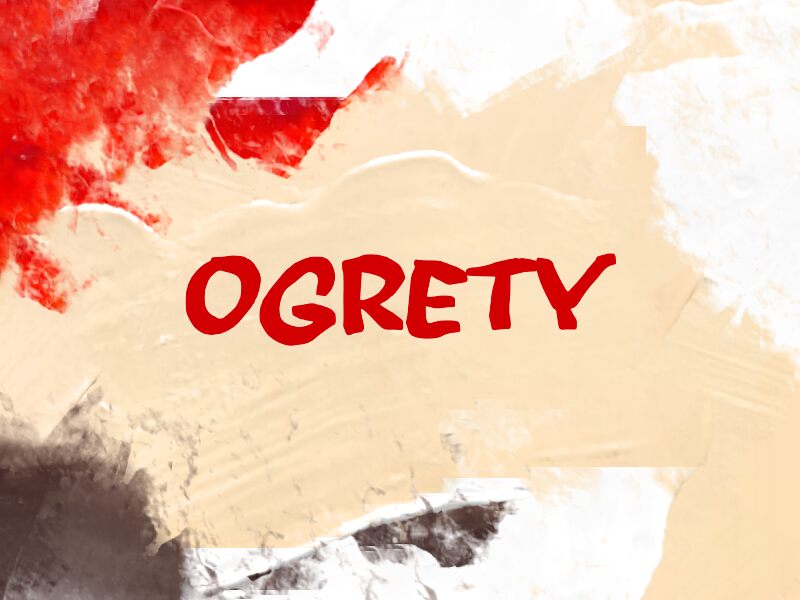
OGRETY
Ogrety od Wep je bezplatné písmo v štýle graffiti s mohutnými, ručne maľovanými siluetami. Pôsobí ako rýchly ťah sprejom na stenu a nie ako niečo kreslené podľa mriežky. Zaoblené tvary, rázne oblúky a nepravidelné okraje dodávajú písmenám uvoľnený streetový rytmus, ktorý si zachováva súdržnosť a nepôsobí chaoticky.
Táto výrazná maľovaná textúra sa skvele hodí na nadpisy plagátov, skate grafiku, obaly albumov, ziny či nálepky, kde je surový tagový vzhľad dôležitejší ako uhladenosť. Krátke názvy a logotypy obzvlášť ťažia z jej bacuľatých, štetcových foriem, ktoré si udržujú svoj charakter aj pri jednoduchej sadzbe.